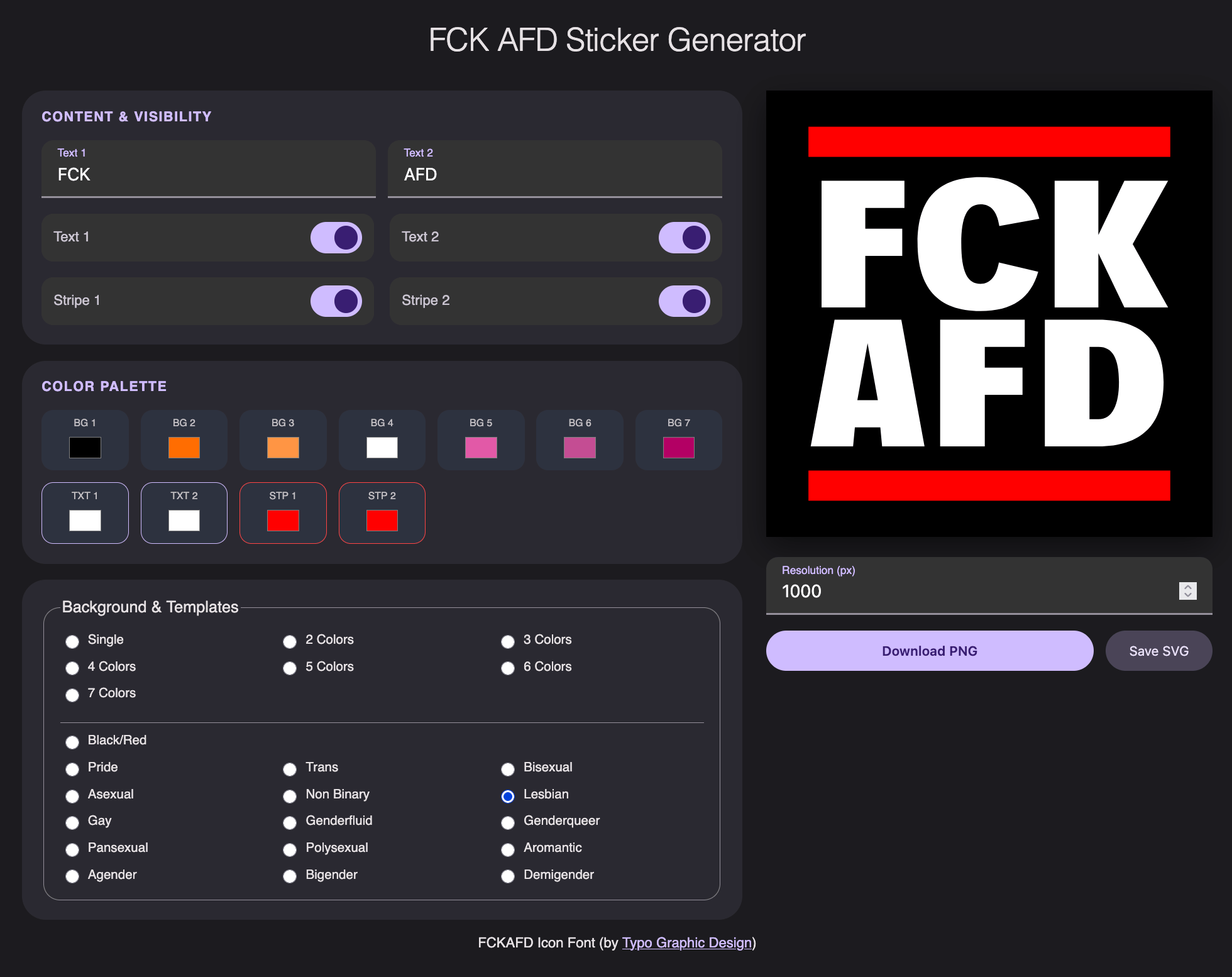
Die FCKAFD Icon-Font is exclusively * designed from 2024 for the font foundry Typo Graphic Design by Manuel Viergutz & Raban Ruddigkeit als ein politisches Statement. DANKE an Dirk Uhlenbrock (LIBERTÉ EGALITÉ FCKAFD) & Chris Campe (AFD? ALTER NEE!) & arrel (LIBERTÉ ÉGALITÉ FCKAFDÉ) & ckreativ
Die Display-Schrift ist eine Sammlung mit 70+ Vektor Slogans für die nächste Demonstration.
■ Schriftname: FCKAFD – Icon Font
■ Font Kategorie: Display Schrift für Überschriften
■ Glyphen-Set: 100+ Glyphen (A–Z & 70+ icons als Vektor Slogans)
■ Design Datum: 2024
■ Schriftgestaltung: Manuel Viergutz (DANKE an Raban Ruddigkeit & Dirk Uhlenbrock)